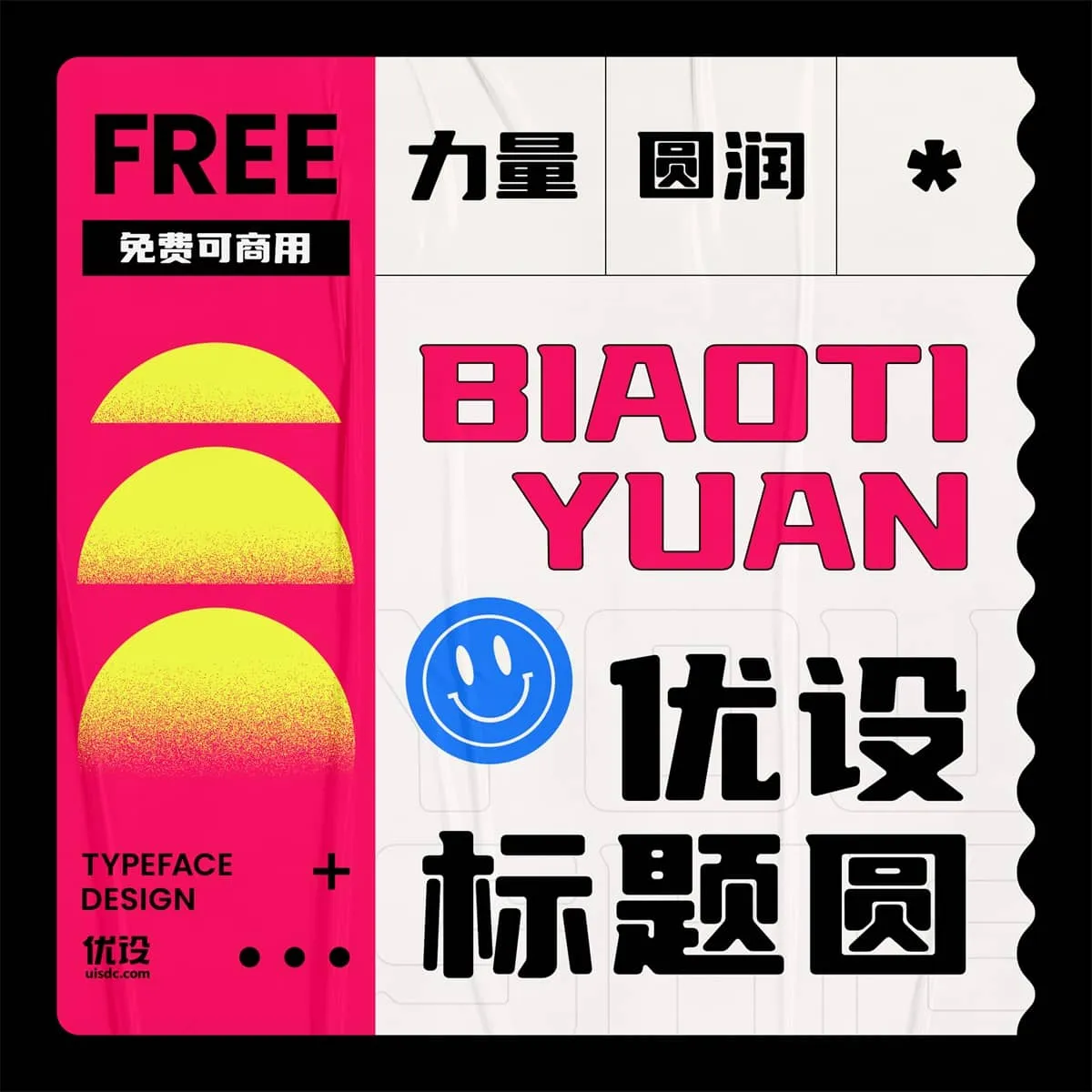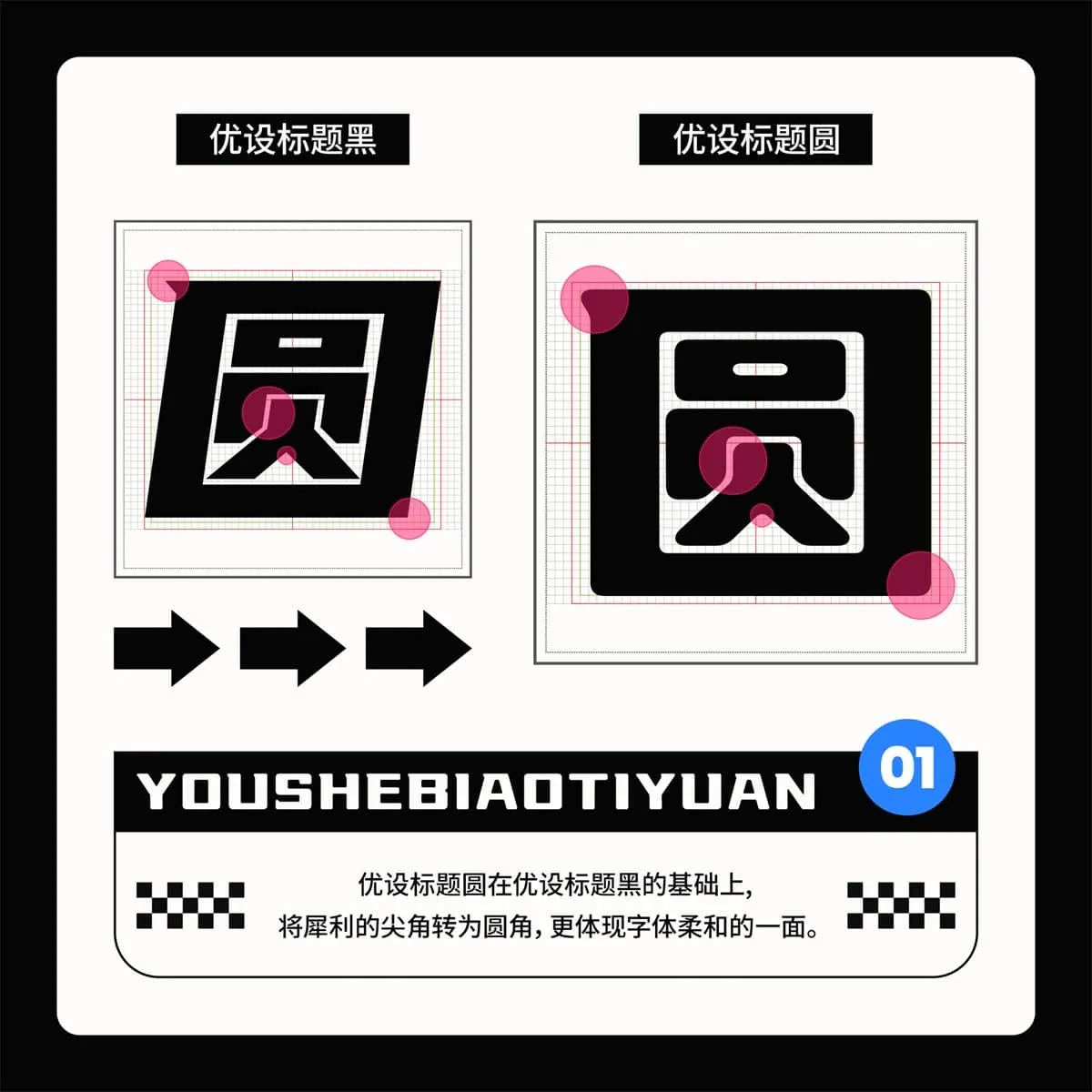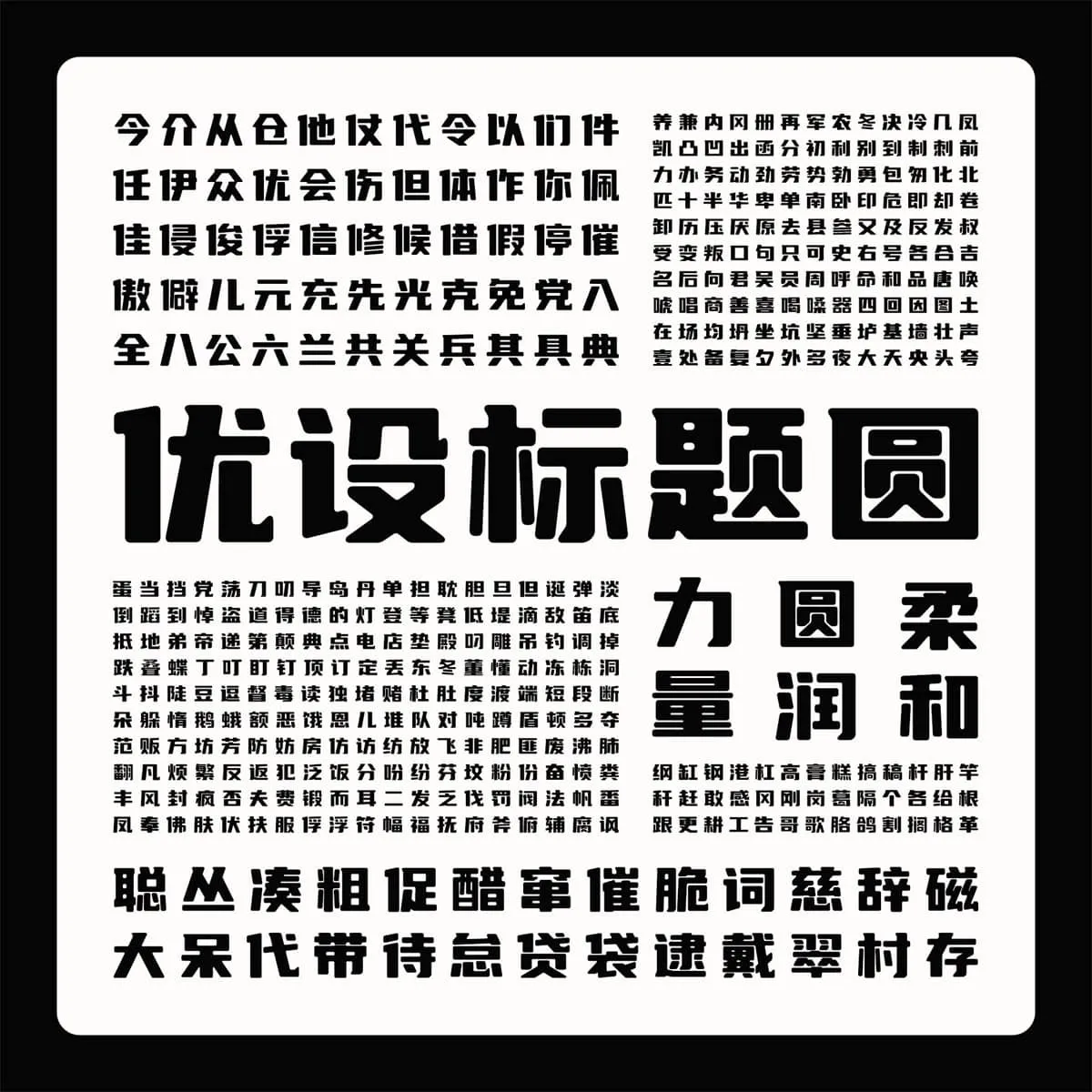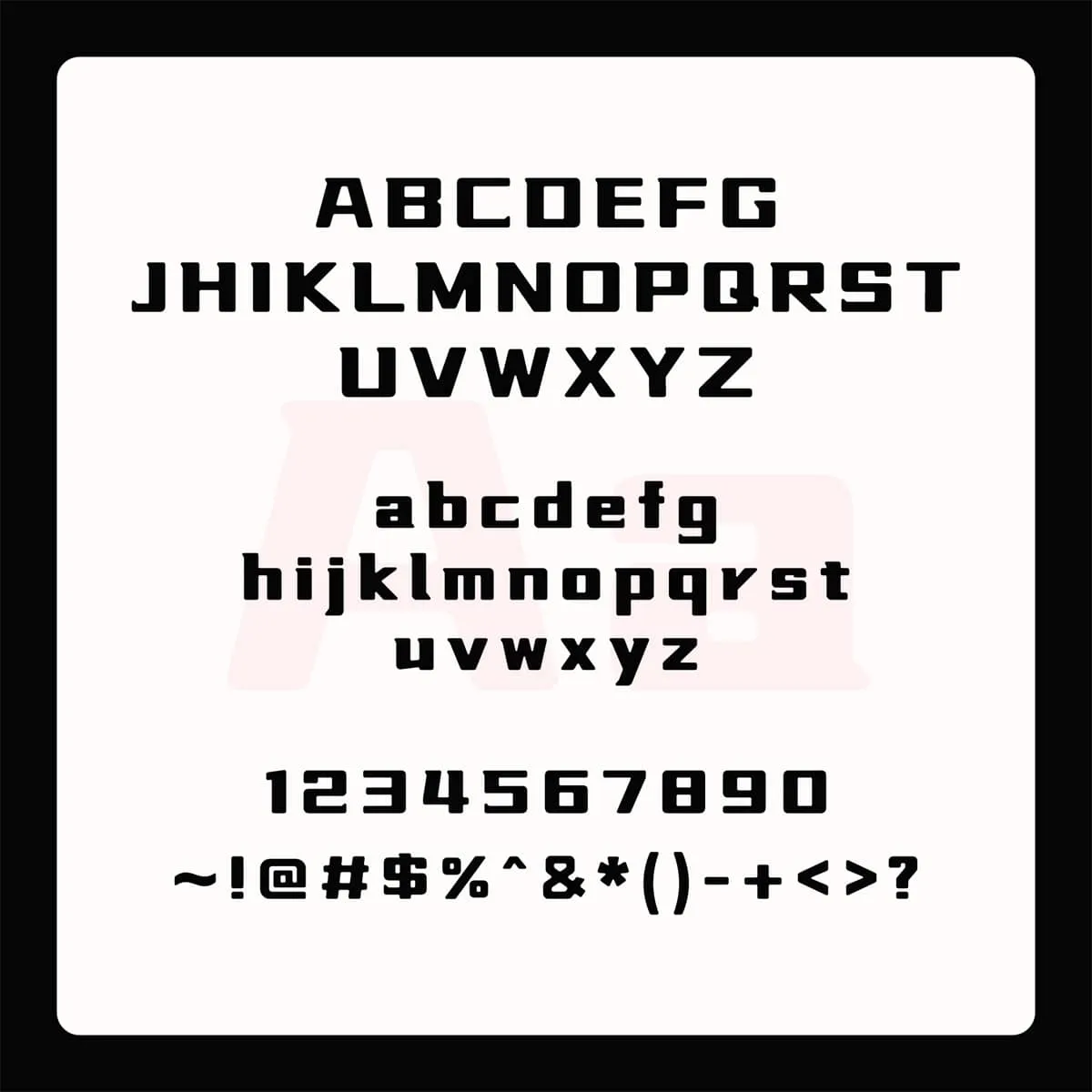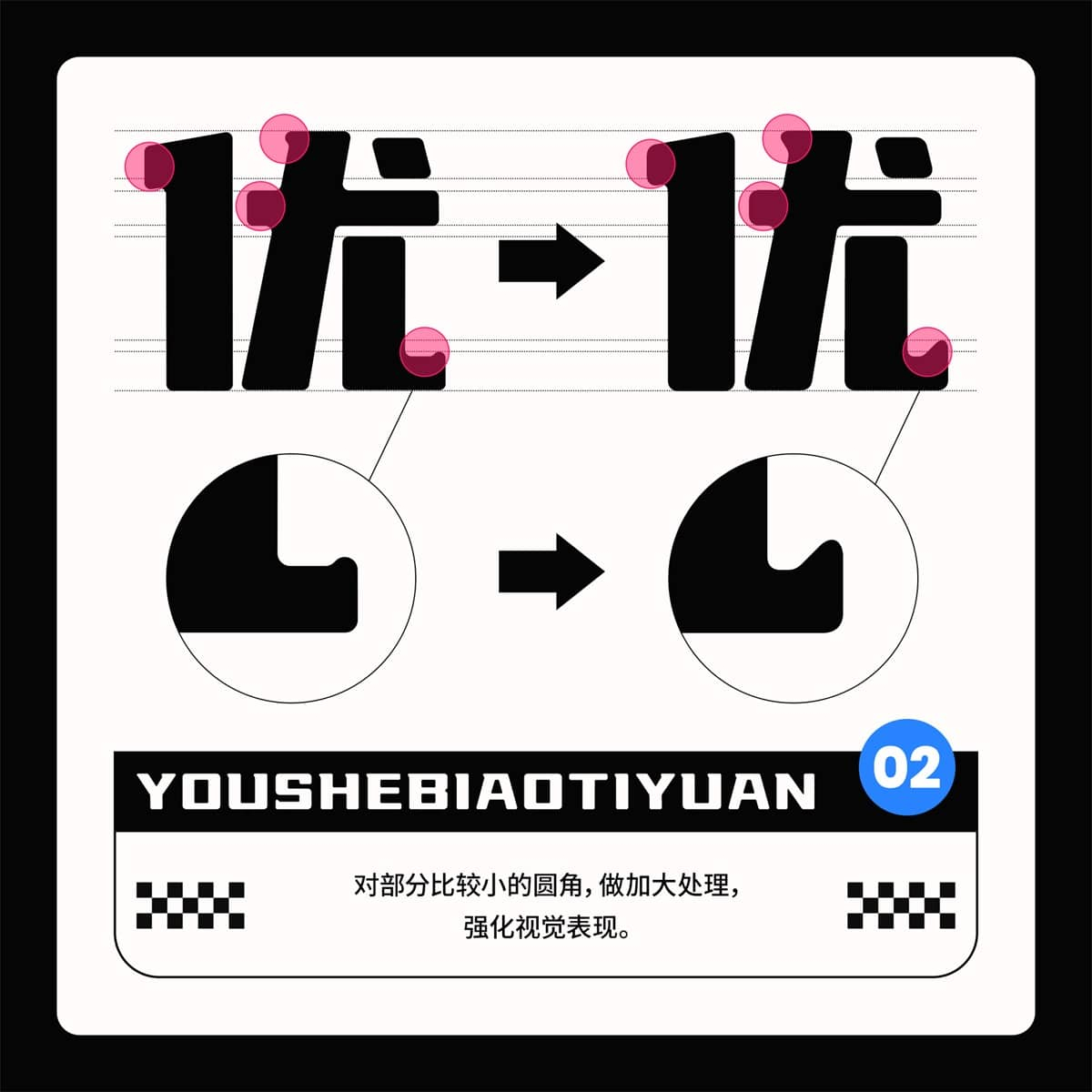
優設標題黑,因其速度感和力量感兼具的特點,作為標題字體再合適不過,一度成為許多設計師的最愛。
但這兩年我們也觀察到一個現象:大家在使用標題黑時,有概率會將它調正進行使用,多方調研和討論後,我們決定在「優設標題黑」的基礎上做一個全新的版本,讓它的使用範圍更加廣泛。
作為「優設標題黑」的兄弟版,這款字體在保留「優設標題黑」的力量感的基礎上,將8°傾斜去除,從斜體變為正體,減弱速度感,增加穩固的感受:
同時將尖角改為圓角,讓其更適用於溫和的宣傳廣告和產品包裝設計:
字體整體風格與標題黑形成直接對比,一個剛毅,一個柔和。